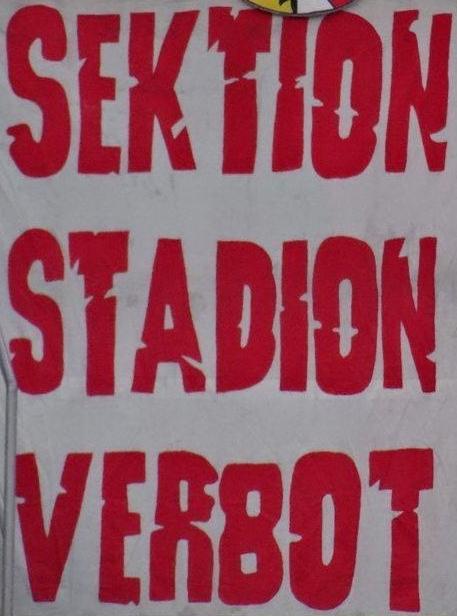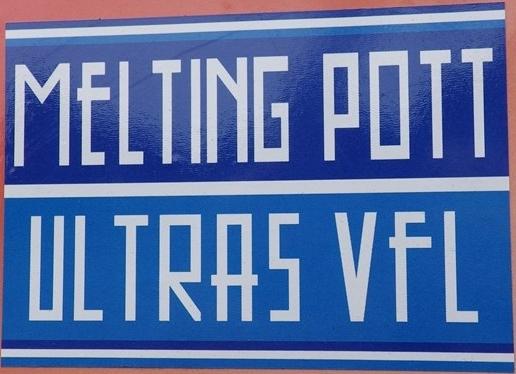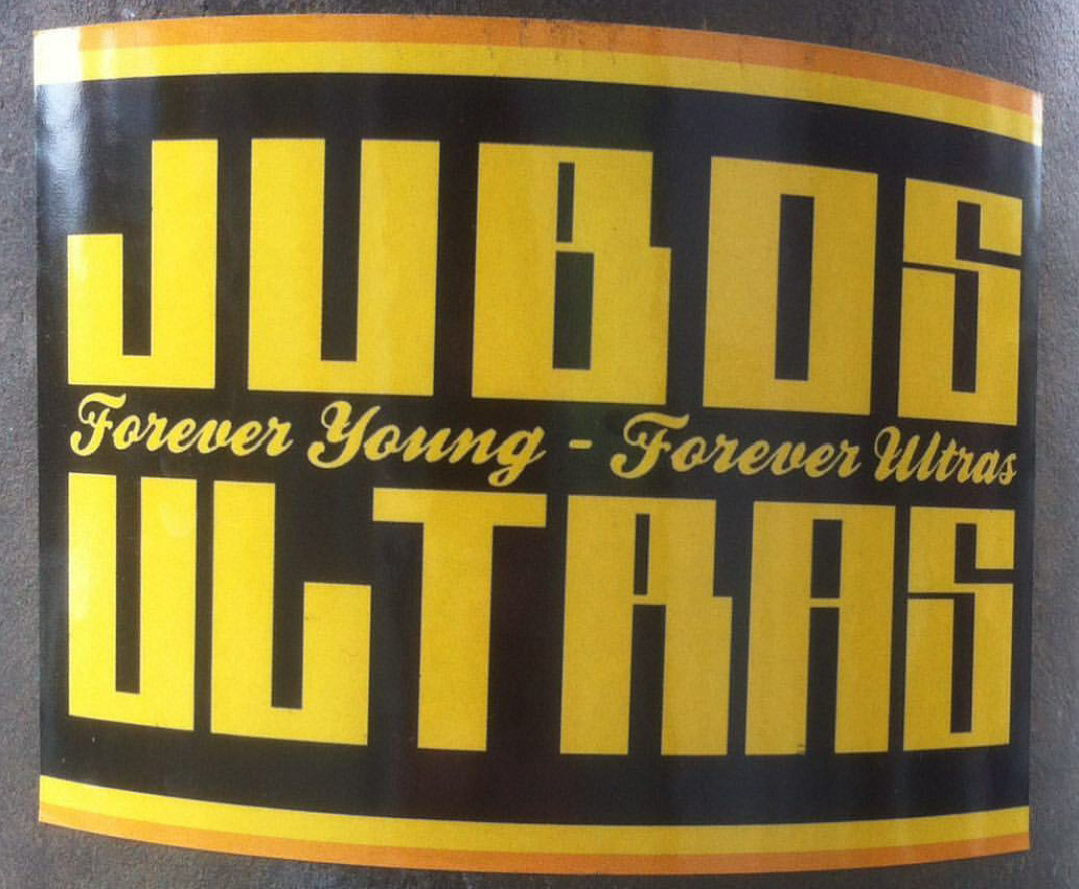
Suche verschiedene ULTRAS Schriftarten
Ich suche die hier die verschiedenen Schriftarten die man auf den 4 Bildern sehen kann und bin für jede Hilfe dankbar.
Die Bilder hab ich teils von google und teils selbstgemacht.
Ob die Schrift was kostet ist mir eigentlich relativ egal, wichtig wäre ersteinmal überhaupt zu wissen um welche Fonts es sich handelt.
Habe mich selber schon durch knapp 400 Seiten Dafont geklickt aber leider noch nichts gefunden.
Bei dem JUBOS interessiert auch nur der JUBOS ULTRAS Font, der in der Mitte ist bereits bekannt.
P.S. Ich habe absolut keine Lust über Ultras etc. zu diskutieren, mich interessieren einfach nur die Schriftarten.
Das erste (Sektion Stadion Verbot) ist handgemacht, zu erkennen an unterschiedlichen gleichen Buchstaben N, S etc.
Melting Pott ist wohl aus mehreren Fonts zusammen gebaut
Mecha Condensed (Regular)  und Avenida Std (Regular)
JUBOS ULTRA mit nacharbeiten eventuell die hier
joe Bob straight (Regular)
Ich sammel Schriftarten für verschiedene Zwecke, auch nicht nur Schriftarten aus dem Fussball Bereich, allerdings muss man erwähnen das die Ultra Szenen was Schriftarten betrifft einen ziemlich guten Geschmack haben.
De gustibus non est disputandum
Außerdem erscheint mir die Szene zu heterogen – wie man an den Beispielen oben schon sehen kann – als dass man eine solche allgemeine Aussage machen kann :-?
Auffallend oft sieht man zwar diese arg geometrisch konstruierten Schriften. Da kann ich mir aber auch vorstellen, dass es dabei nicht nur um die Ästhetik geht sondern diese rein pragmatisch entstanden sind. Das hat sich dann wahrscheinlich verselbständigt und wurde dan quasi symbolisch für die Szene (ähnlich wie Stencil-Schriften für den Military-Bereich) aber es gibt ja auch Ausnahmen.
Antwort kommt zwar spät aber besser als nie . Der Font vom Nürnberg Sek.SV überhänger ist "Godzilla "